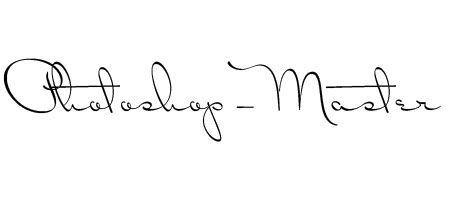
люблю такие))
Почти как я пишу +()
как врач писал
хороший... я им тоже подписывался :)
очень красивый шрифт *_____________*
я ним подпись на своих работах делала =)
Красотень) ♥
норм шрифт
Очень красивый шрифт. *ОООООО*
Спасибо !!! Необычно-симпатично.
Отличный шрифт!
пркольный шрифт
классный шрифт, спасиб =)